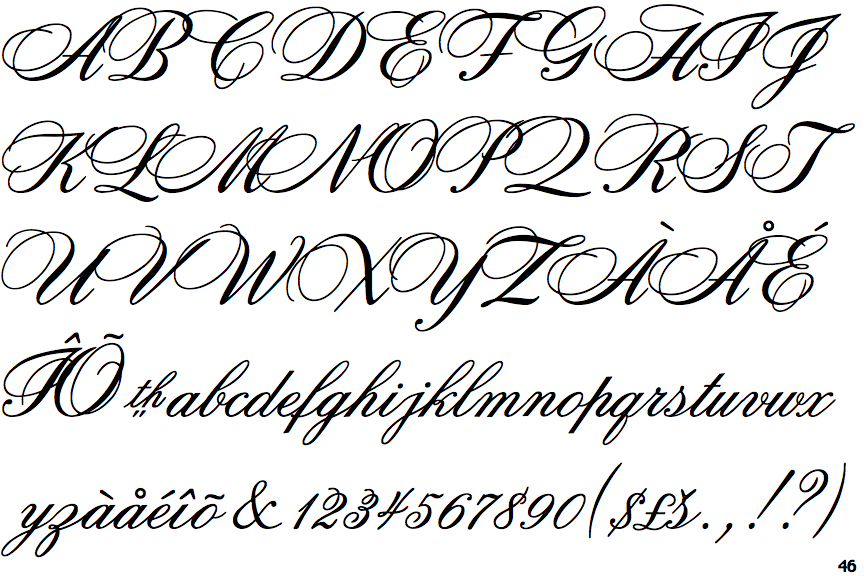
Кириллический шрифт — MONIQA
Красивый шрифт для фотошопа русский прописью. Русские рукописные шрифты. Сделать свой русский рукописный шрифт
На днях наша группа столкнулась с серьезнейшей проблемой — за пропуски пар надо сдать рефераты, написанные от руки.
Вот эта подборка из 80-ти русских рукописных шрифтов. В архиве вы найдете следующие (и др.) экземпляры:
Сделать свой русский рукописный шрифт
Но, скачав эти шрифты, стало понятно, что никто не поверит, будто мы пишем, как Пушкин, Боярский или Моцарт. Поэтому пришлось сделать рукописный шрифт самим. Но как сделать свой шрифт, как две капли воды похожий на ваш обычный почерк?
Далее, на чистом листе (в линейку и в клетку не подойдут) пишем все буквы русского (английского, и других при необходимости) алфавита, а также цифры и спец. символы.
Следующий этап в Font Creator:
— Нажимаем файл — новый (New)
— Даем название своему рукописному шрифту (например Moy_shrift), ставим отметку на Unicode, на Regular и на Don’t include outlines (для чистого бланка силуэтов), короче, все по умолчанию.
— Перед вами появляется панель с силуэтами знаков препинания и английских букв. Вам необходимо вставить в нее Кириллицу. Поступаем следующим образом:
2. Перед вами появляется таблица символов первого шрифта в вашей базе, Затем листаем страницы таблицы кнопкой Block→.
3. Находим русские буквы.
5. Смотрим индекс первой буквы А (у меня $0410) в поле Выбранный Символ (Selected Character).
6. Смотрим индекс буквы я (у меня $044F)
7. В поле Добавьте эти символы (Add these character…) вводим эти числа (как $0410-$044F).
8. Нажимаем Ok.
9. Ваш шаблон пополнился соответствующими силуэтами Кириллицы.
10. Так же вы по отдельности можете вставить туда интересующие вас знаки (Ё,ё и пр.
Теперь нажимаем на силуэт буквы которую хотите сотворить правой кнопкой мыши.
Затем выбираете пункт импорт изображения (Import image).
В разделе Import image вы нажимаете на кнопку Загрузить (Load).
В следующем окне вы открываете папку, в которой сохранили написанные буквы и символы.